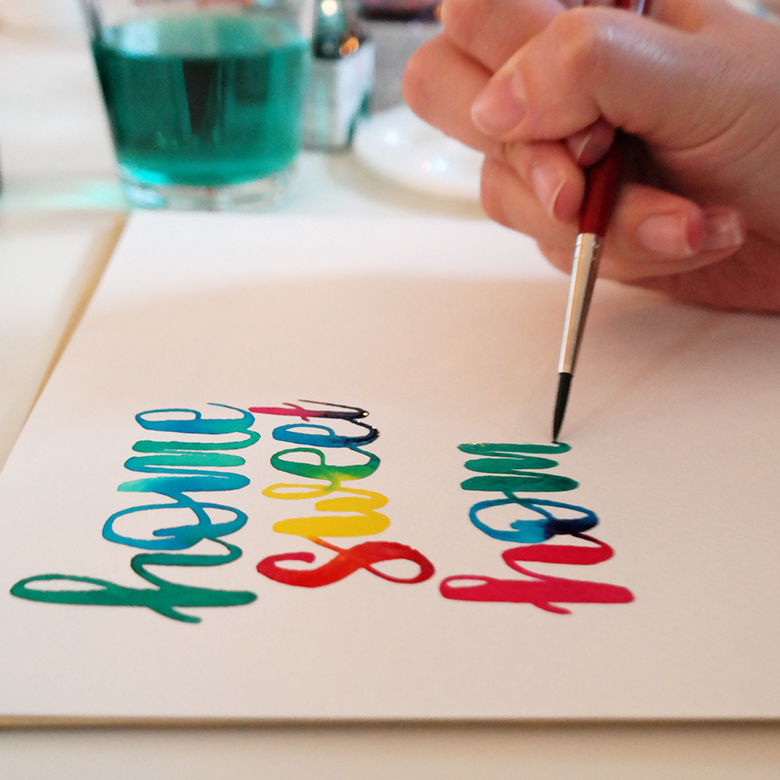
Watercolor Lettering Workshop
In diesem Workshop arbeiten wir mit Pinsel, Farbe und Wasser. Ich liebe den Zauber von Wasserfarben – der Moment in dem Wasser und Farbe sich auf dem Papier vermischen. Ich bin keine Expertin im Bereich Aquarell Malerei, aber mit Buchstaben kenne ich mich verdammt gut aus und genau damit beschäftigen wir uns in dem Workshop! Ich zeige euch wie ihr Buchstaben und kleine einfache Illustrationen mit Wasserfarbe aufs Papier zaubert.
Inhalt des Lettering Workshops:
Als erstes wird eine kleine Einleitung zu Papier, Pinsel und Farben geben. Ausgestattet mit Pinsel und Wasserfarben starten wir mit kleinen Fingerübungen, um ein Gefühl für den Pinsel zu entwickeln. Danach üben wir das Buchstabenpinseln von A bis Z in klein und groß. Dann geht es an Aquarellpapier und Mischpalette, um mit Wasser und Farben zu spielen. Wir pinseln aus Buchstaben Worte und aus Worten Sprüche. Bring dir gerne deine liebsten Worte und Zitate mit – selbstverständlich gibt es aber auch eine Liste mit Inspirationen. Zum Schluss lernst du, wie du dein Lettering mit ein paar kleinen und einfachen Pinselstrichen verzieren kannst. Und mit dabei: Viele nützliche Tipp & Tricks zum Weitermachen.
Watercolor Lettering Workshop Titelbild. Schöne Buchstaben aus Wasserfarben gemacht
Nützlich ist es, wenn du bereits Erfahrungen mit Brushpens und/oder Pinsel gesammelt hast, aber auch Anfänger* sind herzlich willkommen ihre ersten Erfahrungen mit Pinsel und Wasserfarbe zu machen und werden von mir tatkräftig unterstützt.
In dem Workshop wirst du mit Allem ausgestattet, was du zum Buchstabenpinseln brauchst: Von Pinsel über Wasserfarben, passendem Papier, Mischpalette und einem kleinen Hand Lettering Guide, der Anleitungen sowie kleine Inspiration enthält.